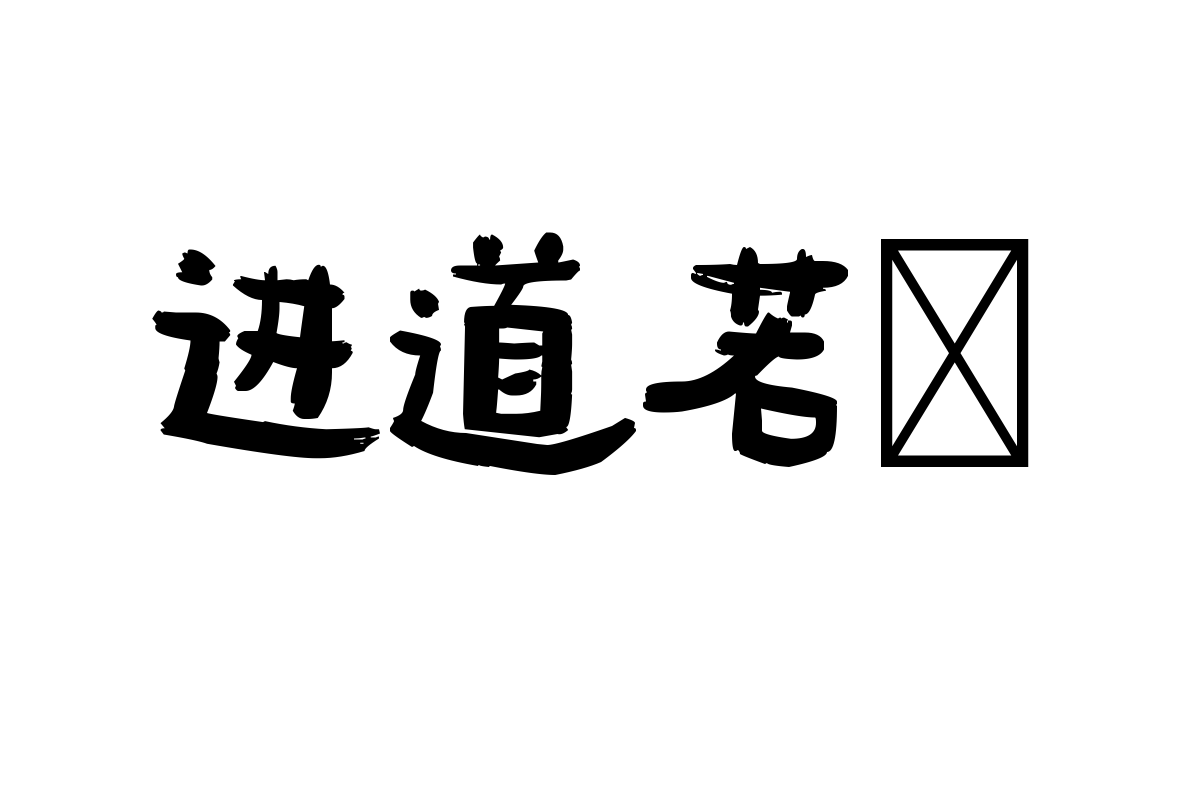
拙影体是一种具有独特风格和特点的字体,它以其独特的笔画结构和笔触感而受到许多设计师和艺术家的喜爱。这种字体的设计灵感来源于中国古典文学中的诗词、书法和绘画,因此它具有浓厚的文化气息和艺术韵味。
拙影体的笔画粗细不一,既有粗犷豪放的感觉,又有细腻柔和的韵味。它的结构紧凑,线条流畅,给人一种强烈的视觉冲击力。同时,拙影体的笔画之间也有一定的空间,使得整体看起来更加和谐自然。
此外,拙影体还具有一定的个性和特色。它的每个字都有自己的特点,有的圆润饱满,有的棱角分明,有的飘逸潇洒,有的沉稳厚重。这种个性化的设计使得拙影体在众多字体中脱颖而出,成为了许多设计师的首选。
总的来说,拙影体是一种具有独特魅力和艺术价值的字体。它不仅能够为设计作品增添美感和个性,还能够表达出设计师对传统文化的理解和尊重。